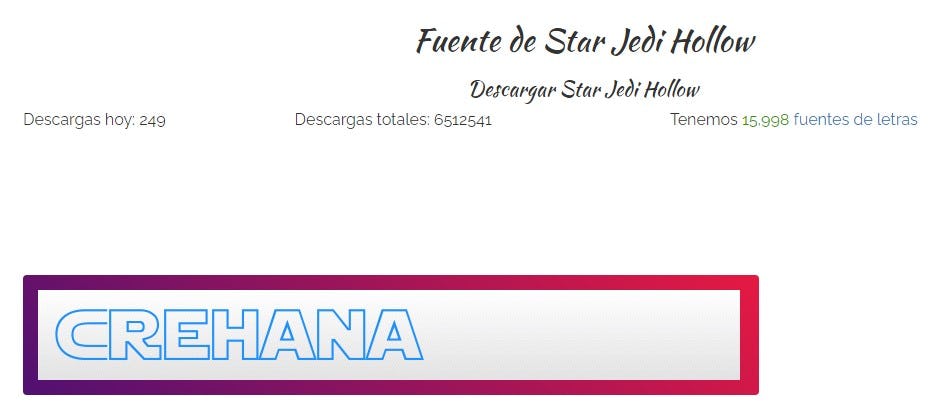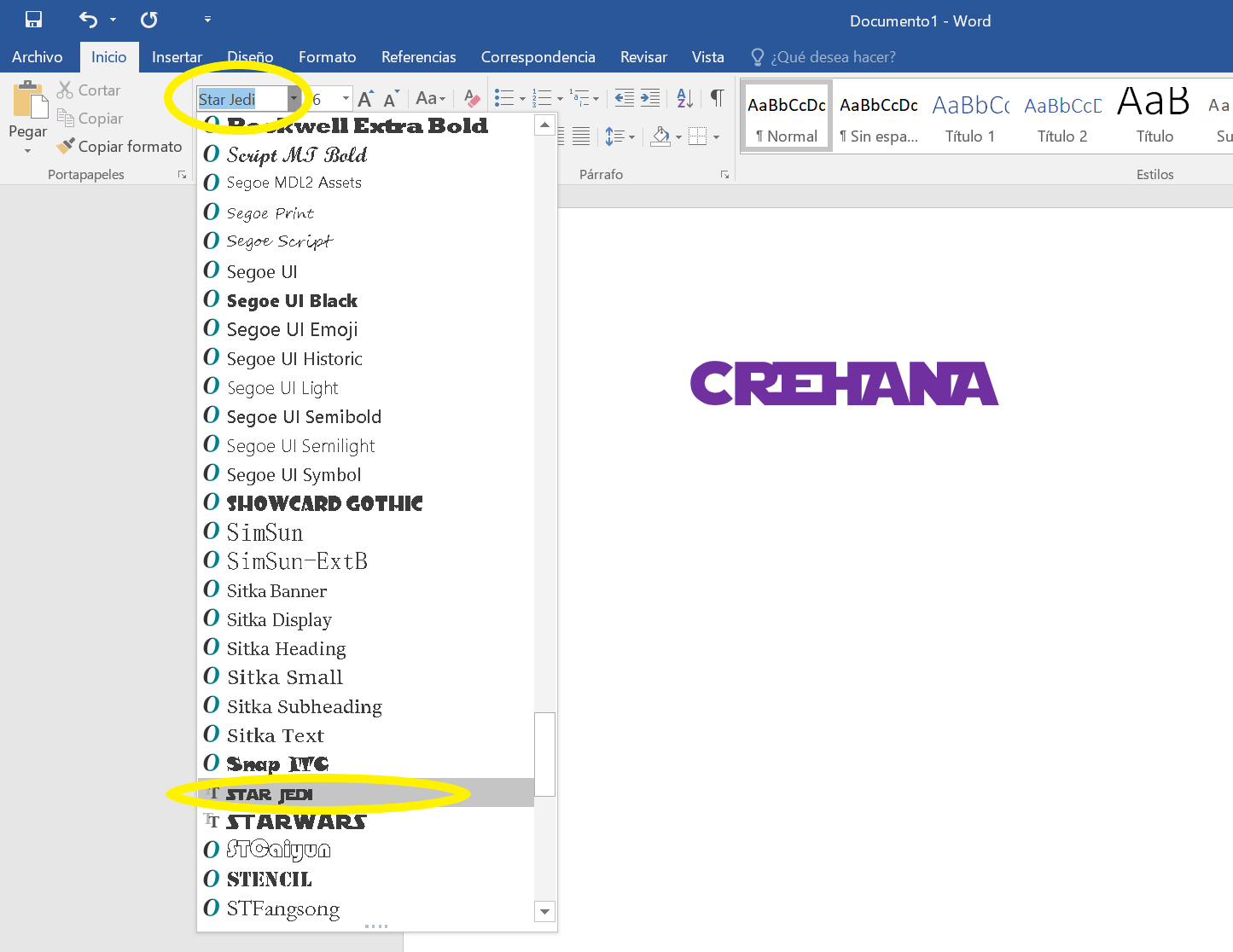
¿Sabías que es posible encontrar las Star Wars Fonts para descargar y utilizar en Word o PowerPoint? Así es, joven Padawan, has llegado al lugar correcto de la galaxia. Te presentaremos 7 tipos de Star Wars Font que podrás encontrar online.
¿Estás listo para llevar tus diseños a una galaxia muy, muy lejana? ¡Que la ‘fuente’ te acompañe!
¿Qué es una Star Wars font?
Primero, contextualicemos y definamos mejor. Si leíste el título y pensaste: ¿qué es una font y por qué está al lado de Star Wars? No te alarmes, una font se refiere al término “fuente” en inglés. En tipografía, se le denomina font o fuente a un grupo de caracteres que tienen un diseño en particular y se diferencian del resto.
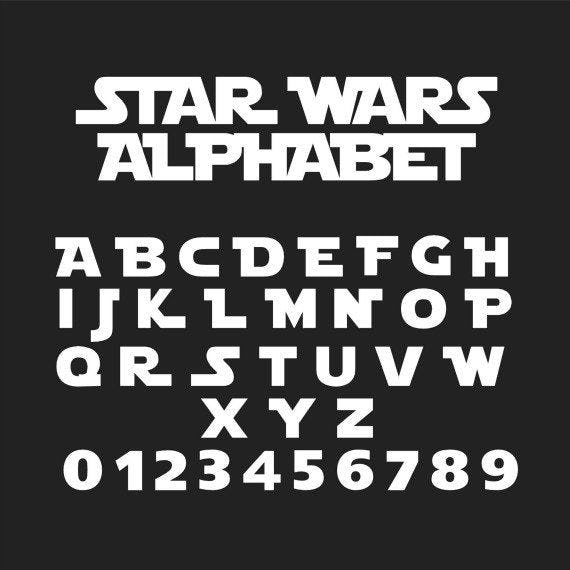
Así que, sí, tenemos fuentes de Star Wars listas para que puedas usarlas en todos tus diseños, documentos o lo que consideres necesario. Para un fan de la saga nunca es suficiente, ¿verdad?
Entonces, ¿qué es una Star Wars font? A lo largo de los años, la saga de Star Wars ha ido evolucionando no solo en su contenido e historia, personajes y escenarios. Sino también en el diseño de las letras de cada afiche publicitario para sus películas o videojuegos.
A continuación, te presentamos el logo original con la primera Star Wars font, ¿Sabías que esta font se diseñó a mano?
La artista Suzy Rice se inspiró en la fuente Helvetica Black para crear el icónico logo, luego, el diseñador Joe Johnston hizo pequeños cambios para perfeccionar el logo hasta convertirlo en el que conocemos actualmente (te contamos la historia más adelante).
La tipografía Star Wars ha cambiado en cada película, sin embargo, siempre han mantenido la esencia y los rasgos más específicos de la primera Star Wars font. Cada una de estas tipografías de Star Wars ha logrado destacarse por sí sola, tanto que cualquier fanático de la saga podría identificar a cual película corresponde cada fuente.
Conoce las Star Wars fonts disponibles
Después de leer este artículo no tendrás excusa para que cada diseño, presentación o documento que crees luzca como sacado de una película.
Star Jedi Font
La clásica e icónica tipografía de Star Wars directa para descargar e incluir en cualquier proyecto creativo. Aquí el diseñador Boba Fonts ha recreado perfectamente la Star Wars font "Jedi" propiamente conocida como Star Jedi. Reconocible a simple vista esta fuente te ayudará a que tus diseños no pasen desapercibidos. El diseñador de esta Star Wars font creó tres variaciones por lo que puedes elegir la que más te guste.
Mandalorian Font
Según el propio diseñador, esta fuente es una réplica exacta del lenguaje mandaloriano que se vio en Star Wars Episodio II. También, ha sido vista en el DVD de Star Wars lanzado en el 2004. Sin duda, una fuente esencial para tu colección como conocedor de la saga. Fan que se respeta, tiene hasta las que no entienden la mayoría de personas, ¿no?
Distant Galaxy Font
La Distant Galaxy Star Wars font nos lleva justamente a una galaxia distante y futurista, muy futurista. Todas las variaciones que el diseñador ShyFoundry ha elaborado: desde negritas y cursivas hasta trazos gruesos y símbolos característicos de una civilización del espacio exterior.
Death Star Font
Fiel al estilo de Star Wars en los 80’s, el diseñador SharkShock ha creado esta tipografía un tanto parecida a la letra del logo de Star Wars, manteniendo el estilo retro característico de las primeras películas. Con ella puedes potenciar cualquier diseño que tengas. Comprensible para el público en general, esta tipografía destacará en cualquier diseño que tengas, incluso evocará memorias de los inicios de la saga.
Star Jedi Outline Font
Tal vez Boba Fonts sea aún más fan de Star Wars que tú, querido Jedi. Pues, volvió con la primera Star Jedi font que te enseñamos, solo que mejorada y llevada hacia un estilo más versátil. Lo mejor es que descargar esta fuente de Star Wars sigue siendo gratis. Si te gustó la fuente anterior, te prometemos que esta te encantará también.
Star Jedi Logo Font
Definitivamente las Star Wars fonts se han convertido en nuestras nuevas tipografías favoritas. Nos declaramos fans y estamos contentos de haber encontrado tantas para compartirlas contigo. Sabemos que las usarás sabiamente en tus presentaciones, en tus documentos o en tus diseños. La creatividad no tiene límites.